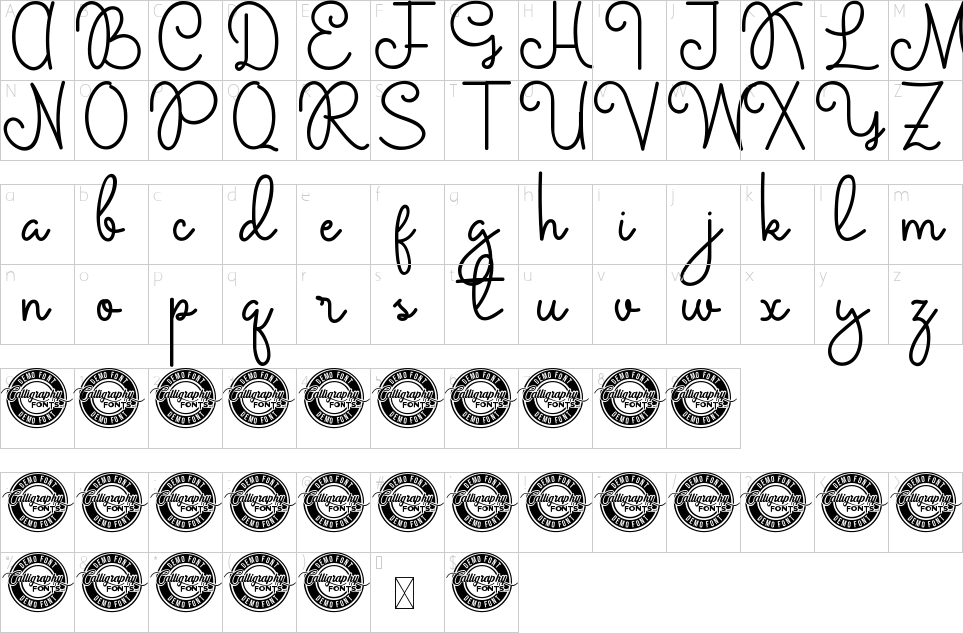
Descubra Madelyn Bright, uma elegante fonte para sua próxima projeto de design. Essa fonte foi projetada por CalligraphyFonts e é uma delícia para usar em qualquer projeto. Com 592 downloads, não há dúvida de que os designers estão apreciando sua beleza e facilidade de uso. Seja para criar um logotipo criativo ou formar uma frase poderosa em uma publicação, Madelyn Bright oferece uma combinação perfeita de estilo e legibilidade. Experimente esta fonte para aprimorar seu design e adicione uma nova dimensão ao seu trabalho. Sua escolha não pode deixar ninguém indiferente.